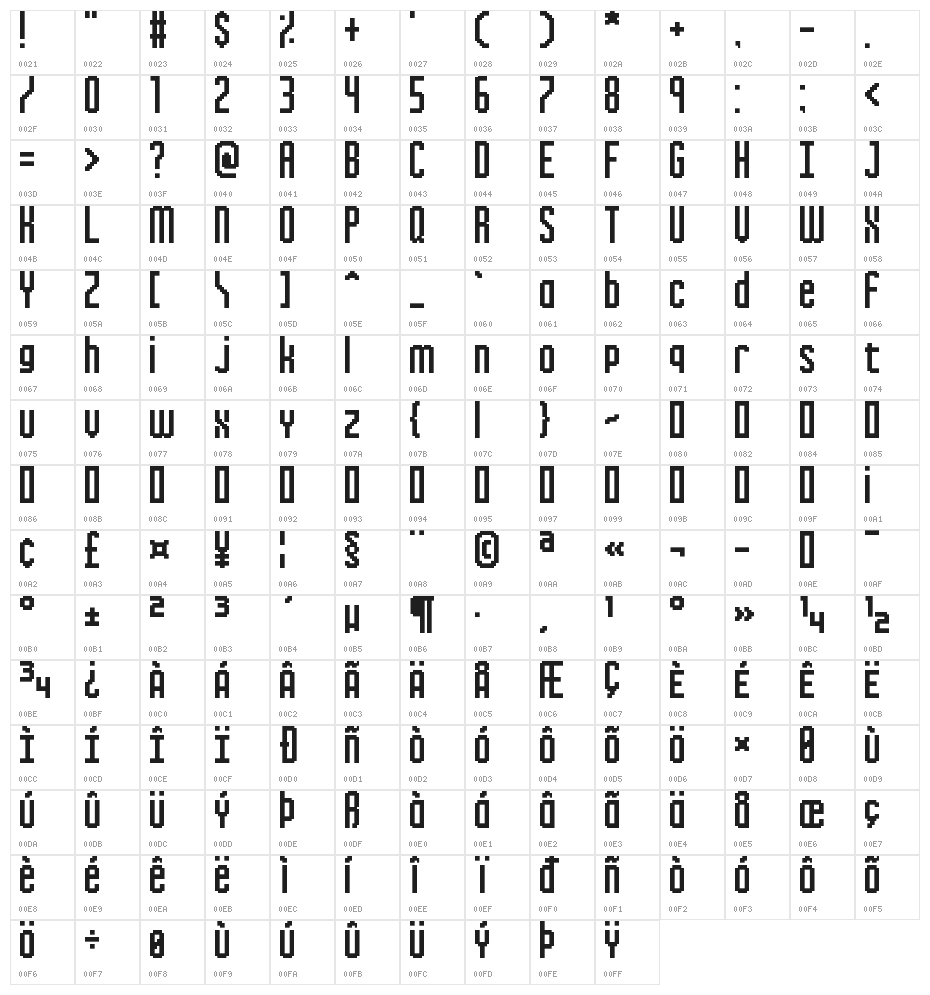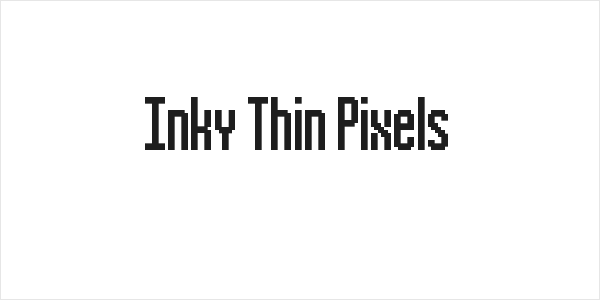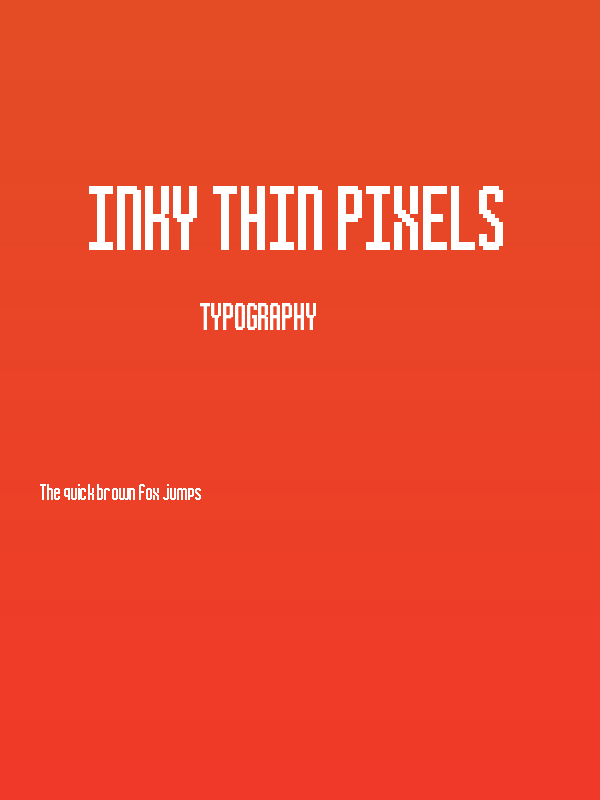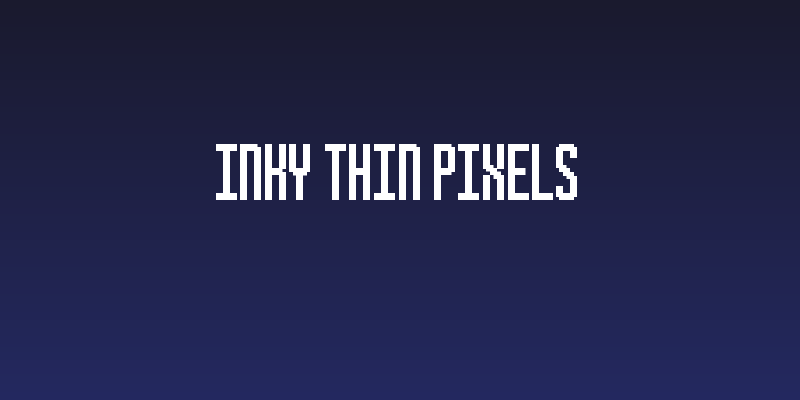
Inky Thin Pixels Font
| Categorii | Pixel |
| Stil general | Retro, Digital |
| Caz de utilizare | Headlines, Logos, Digital displays |
| Proiecte propuse | Ideal for retro video games, digital art projects, tech-themed posters, and nostalgic branding. |